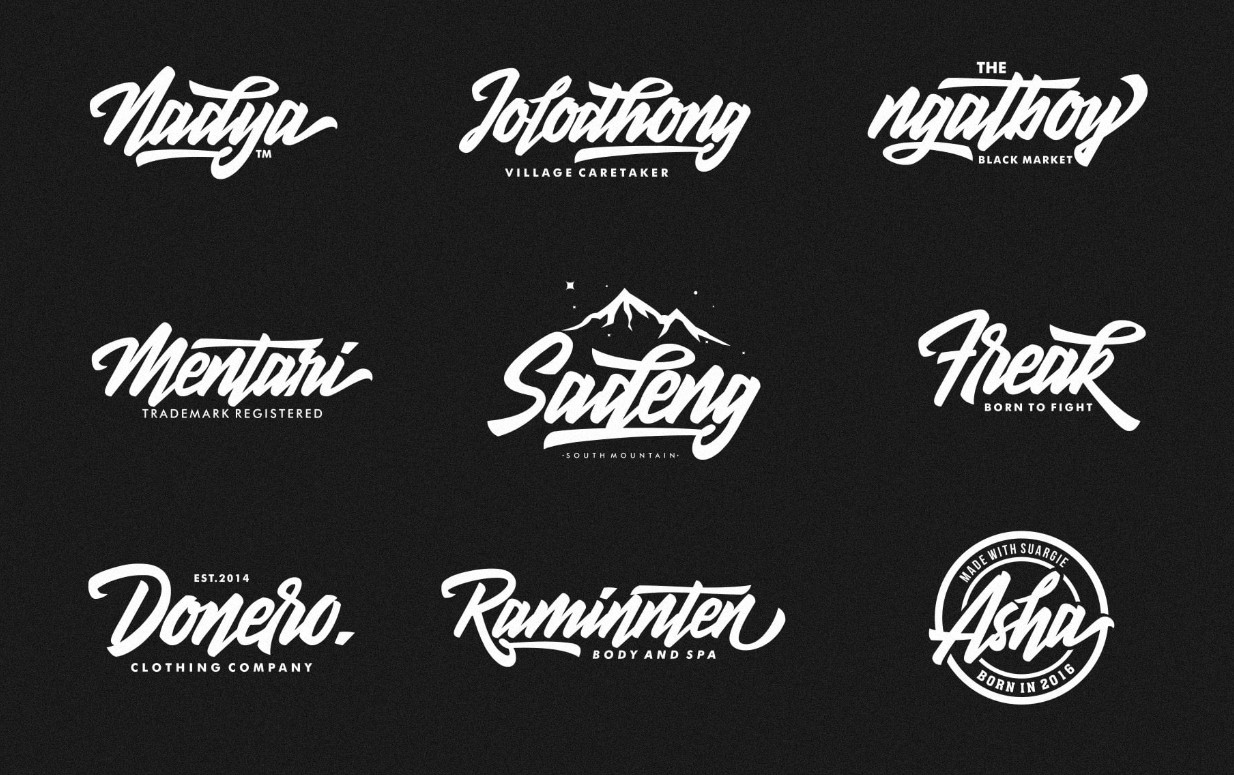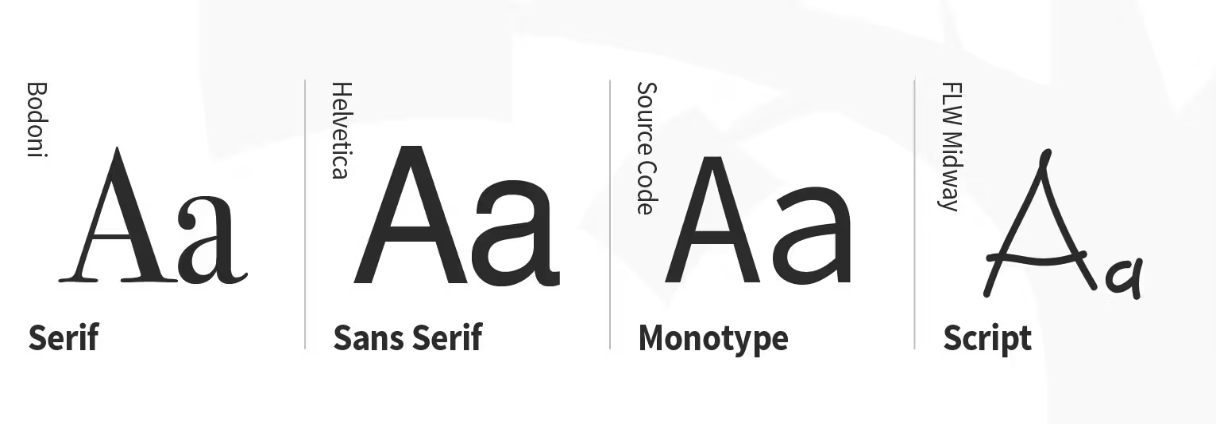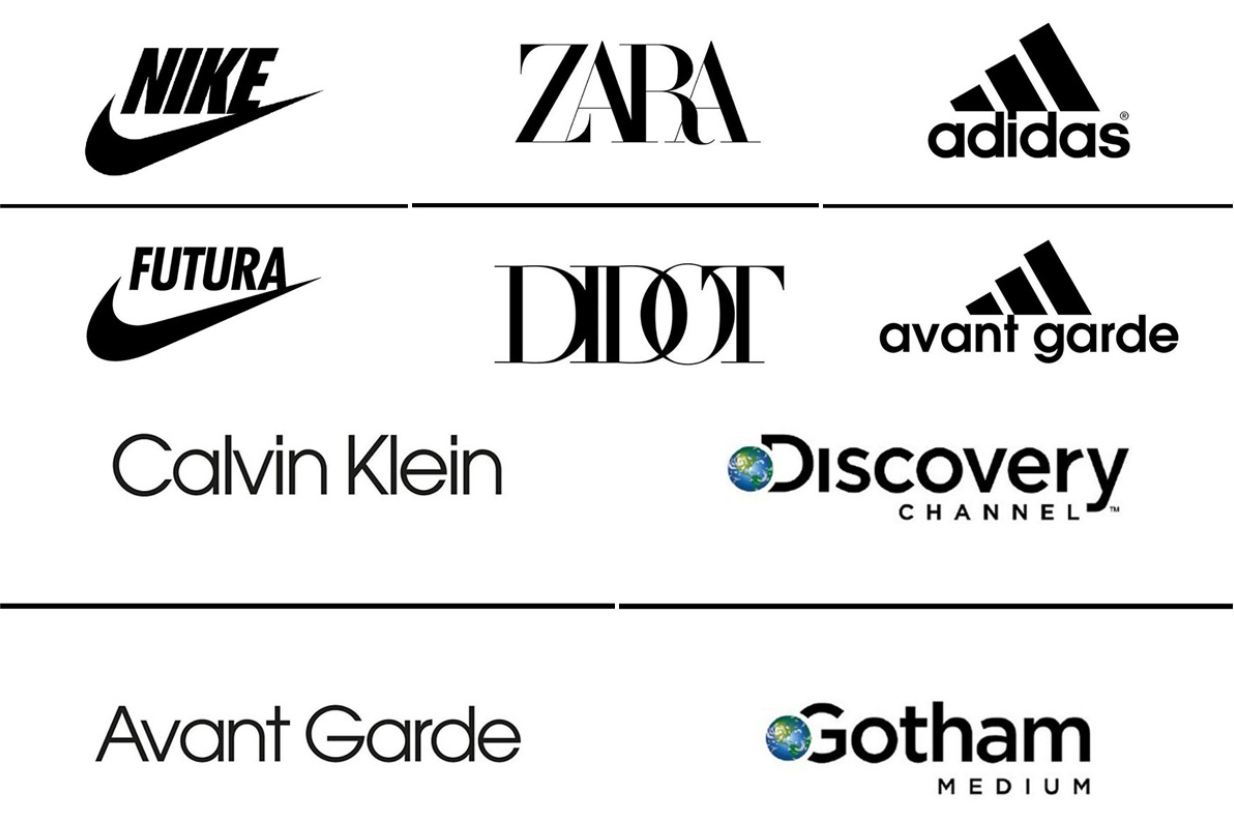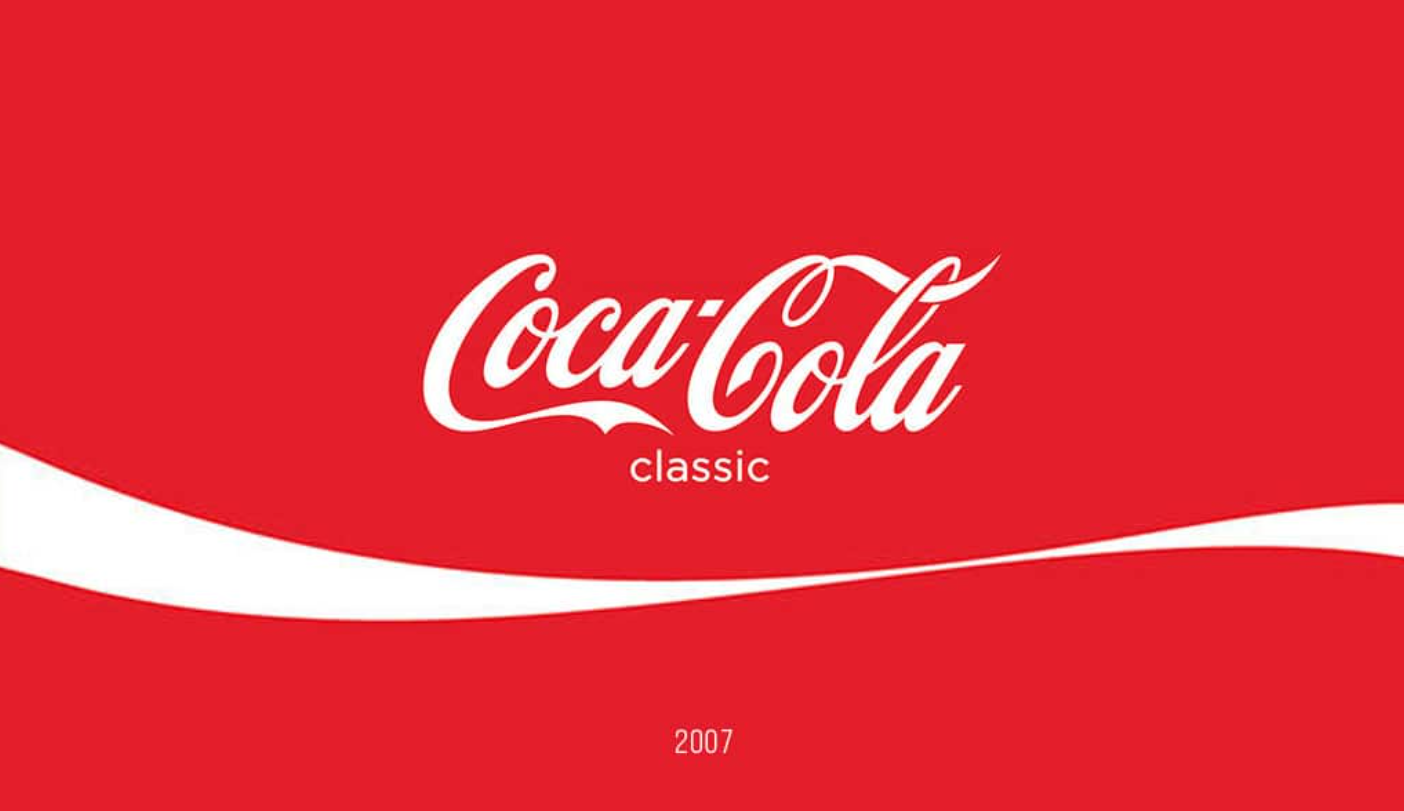
Bí Quyết Chọn Font Chữ: Tạo Logo Độc Đáo Đậm Chất Thương Hiệu
Trong quá trình thiết kế logo, việc chọn font chữ là bước khởi đầu quan trọng giúp định hình cá tính và thông điệp của thương hiệu. Đầu tiên, hãy hiểu rõ sứ mệnh, giá trị cốt lõi và đối tượng khách hàng mà thương hiệu hướng đến để xác định phong cách thiết kế phù hợp.
Bí Quyết Chọn Font Chữ: Tạo Logo Độc Đáo Đậm Chất Thương Hiệu
Logo chính là bộ mặt của một thương hiệu. Chúng ta đều biết rằng trong mỗi thiết kế logo, màu sắc, hình khối và hình ảnh biểu trưng đều có vai trò không nhỏ. Tuy nhiên, font chữ lại mang đến cảm xúc đặc trưng giúp logo trở nên sống động và gần gũi hơn với khách hàng. Qua bài viết này, SaDesign sẽ cùng bạn khám phá những yếu tố then chốt để lựa chọn font chữ sao cho vừa đẹp vừa nổi bật, góp phần khẳng định thương hiệu trên thị trường đầy biến động hiện nay.
1. Lý do font chữ quan trọng trong thiết kế logo
Mỗi font chữ đều có một "tính cách" riêng. Từ những nét gạch mảnh mai cho đến những đường nét đậm dày, chúng có thể tạo ra những cảm xúc khác nhau: sự thanh lịch, hiện đại, truyền thống hay nghệ thuật. Một logo với font chữ phù hợp sẽ giúp khách hàng dễ dàng nhận diện và ghi nhớ thương hiệu. Ví dụ, các thương hiệu thời trang cao cấp thường lựa chọn những font chữ thanh lịch, tinh tế để thể hiện sự sang trọng, trong khi các thương hiệu công nghệ lại hướng đến những kiểu chữ hiện đại, tối giản nhằm tạo cảm giác tiên phong và đổi mới.
Không chỉ dừng lại ở việc truyền tải thông điệp, font chữ còn là yếu tố giúp logo nổi bật giữa hàng ngàn biểu tượng khác. Một font chữ độc đáo, được thiết kế tỉ mỉ sẽ tạo ra một điểm nhấn riêng biệt, góp phần làm tăng khả năng nhận diện thương hiệu. Khi khách hàng nhìn thấy một font chữ quen thuộc, họ sẽ liên hệ ngay lập tức với hình ảnh và giá trị mà thương hiệu muốn gửi gắm. Điều này đặc biệt quan trọng trong thời đại mà người tiêu dùng bị cuốn theo hàng loạt thông tin và hình ảnh đa dạng trên các phương tiện truyền thông.
Hãy lấy ví dụ của các thương hiệu nổi tiếng như Coca-Cola với kiểu chữ script tròn trịa hay Google với font chữ sans-serif tối giản. Mỗi kiểu chữ không chỉ phản ánh được đặc trưng riêng của từng thương hiệu mà còn giúp chúng tạo nên sự khác biệt rõ ràng trên thị trường toàn cầu. Điều này minh chứng rằng, font chữ không chỉ đơn thuần là một lựa chọn thẩm mỹ mà còn là chiến lược định vị thương hiệu.
Với những tiêu chí trên, chúng ta đã có cái nhìn tổng quan về các yếu tố cần lưu ý khi chọn font chữ. Tiếp theo, hãy cùng tìm hiểu chi tiết cách chọn font chữ khi thiết kế logo nhé.
2. Cách chọn phông chữ khi thiết kế logo
Để chọn một phông chữ đẹp và phù hợp với logo thương hiệu không phải chuyện đơn giản. Nếu bạn là một Designer và đang trong quá trình làm quen với công việc hãy tham khảo bài viết này của SaDesign:
2.1. Luôn nắm chắc kiến thức cơ bản
Giống với các ngành đào tạo khác, thiết kế đồ họa cũng có những kiến thức cơ bản cần nắm rõ. Trước khi đi vào quá trình làm logo, bạn cần hiểu rõ về các kiểu chữ đang phổ biến hiện nay như serif, sans serif, script, monospace, display,… Mỗi kiểu sẽ có cách hoạt động của tỷ lệ, hệ thống phân cấp cũng như kerning, tracking, leading,… khác nhau.
Khi không nắm rõ những kiến thức cơ bản sẽ khiến quá trình thiết kế logo gặp nhiều khó khăn. Bởi tùy từng kiểu chữ sẽ phù hợp với thiết kế logo khác nhau. Đây sẽ là thách thức lớn nếu bạn không nắm rõ kiến thức cơ bản.
2.2. Không nên chạy theo xu hướng
Logo thường gắn liền với doanh nghiệp theo năm tháng nên trong quá trình thiết kế, bạn nên chú ý không chạy theo xu hướng hiện tại. Bởi có thể thời điểm bây giờ, phông chữ đó được ưa chuộng nhưng sẽ rất nhanh, một vài năm thậm chí một vài tháng là thay đổi. Lúc này, logo sẽ trở nên cũ và không còn tính ứng dụng cao.
Đặc biệt, xu hướng hiện nay đang hướng tới sự tối giản. Nếu bạn muốn logo mình thiết kế trở nên trường tồn với thời gian hãy nghiên cứu thật kỹ các phông chữ. Đôi khi cơ bản lại là tốt, chúng sẽ trở nên nổi bật và có thể ứng dụng ở bất kỳ đâu, bất kỳ lúc nào.
2.3. Đặt suy nghĩ của khách hàng lên đầu
Nhiều nhà thiết kế thường chạy theo cảm hứng và suy nghĩ của mình mà quên mất khách hàng mới là người duyệt cuối cùng. Trong quá trình thiết kế logo cũng vậy, hãy chủ động hỏi về suy nghĩ và mong muốn của khách hàng. Hãy phác thảo ra những ý chính để từ đó thiết kế logo được nhanh chóng, chính xác và hiệu quả hơn.
Bạn có thể thảo luận với khách hàng để xem nhu cầu thực sự của họ là gì. Trong trường hợp họ muốn một logo đơn giản, trường tồn nên chọn phông chữ cơ bản, tối giản. Nếu khách hàng muốn logo thật độc đáo, khác biệt, nhìn vào là nhớ mãi hãy chọn kiểu chữ cầu kỳ hơn.
2.4. Đơn giản luôn là lựa chọn tốt nhất
Xu hướng hiện nay đang hướng tới sự tối giản, ngay cả việc thiết kế logo cũng vậy. Nhiều thương hiệu không ngần ngại thiết kế lại toàn bộ bộ nhận diện thương hiệu với một logo chỉ có nguyên chữ viết, bỏ hết biểu tượng hình ảnh. Có thể thấy, tầm quan trọng của phông chữ trong quá trình thiết kế logo.
FontSquirrel: Cung cấp các font chữ bản quyền miễn phí và chất lượng cao.
Các trang web khác như DaFont, Behance cũng là nguồn cảm hứng tuyệt vời cho những ai đang tìm kiếm những kiểu chữ độc đáo.
Hãy nhớ rằng, mỗi quyết định trong thiết kế đều có sức ảnh hưởng lớn đến hình ảnh của thương hiệu. Việc lựa chọn font chữ không chỉ là vấn đề thẩm mỹ, mà còn là chiến lược định vị thương hiệu. Hy vọng bài viết này đã giúp bạn có thêm nhiều kiến thức và cảm hứng để tạo ra những thiết kế ấn tượng, đậm chất riêng.